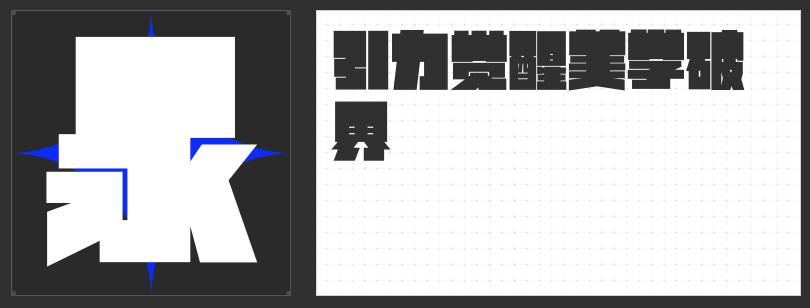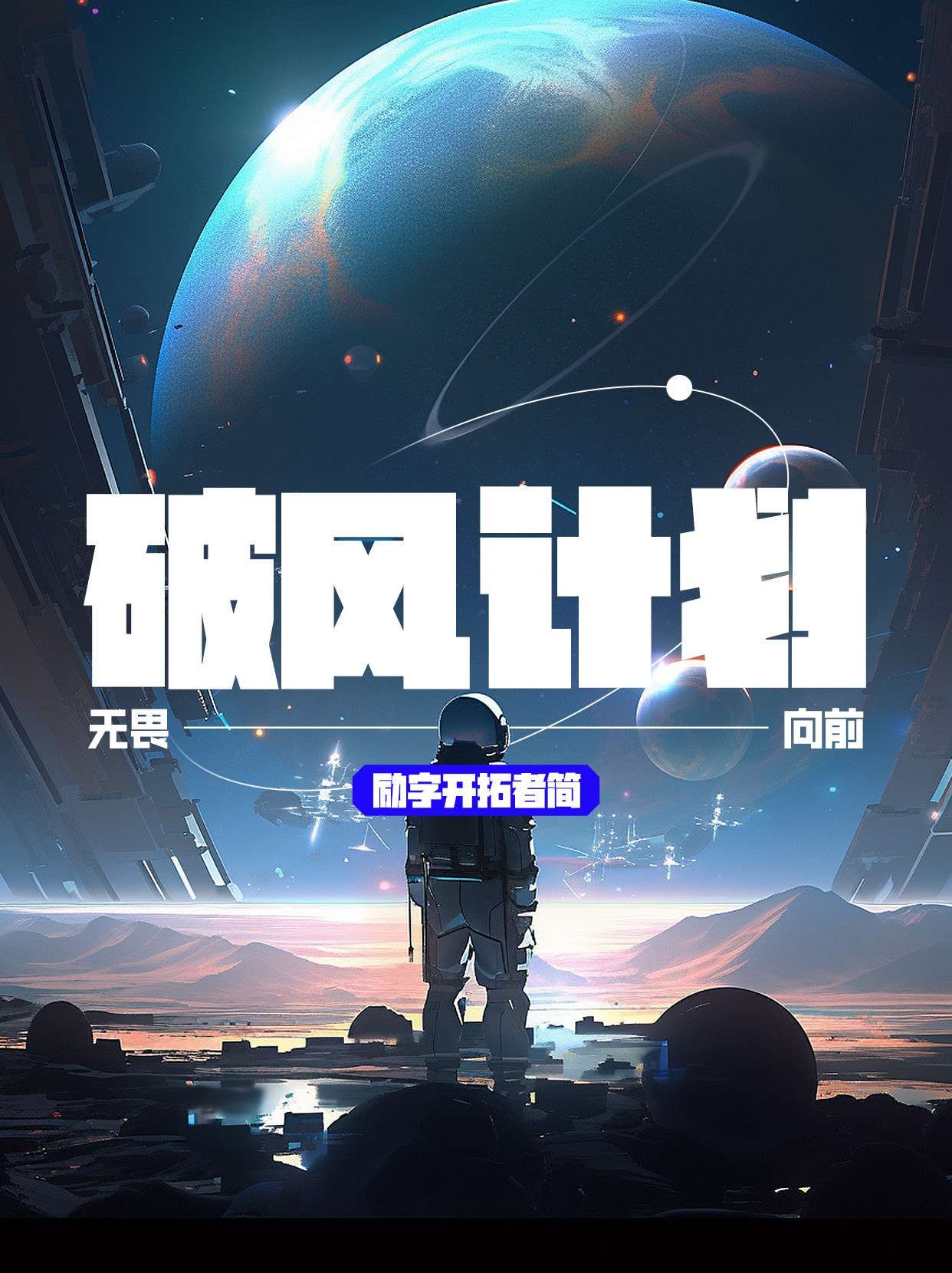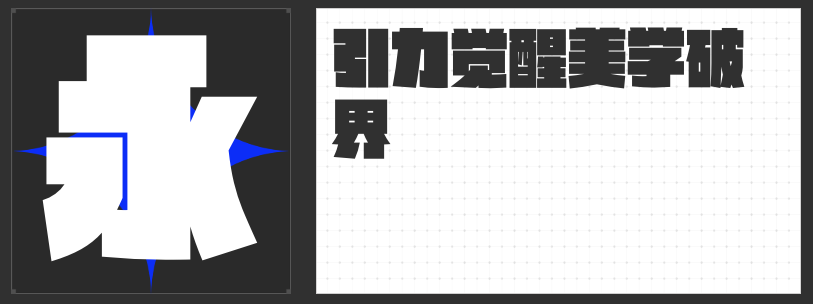
力量感爆棚!四款设计必备强势字体推荐
在设计中,字体不仅仅是文字的载体,更是传递情感与氛围的关键元素。今天,为大家推荐四款充满力量感的字体,它们不仅具备强烈的视觉冲击力,还能在设计中增添一份独特的魅力。
这款字体以其方正的字型和较大的中宫设计,展现出一种稳重的力量感。笔画横平竖直,棱角分明,简约而有力。特别是去钩处理后的笔画,以及竖直处理的撇、捺、点,更是带来了强烈的镜像视觉效果,让文字仿佛拥有了生命。此外,它还包含了众多网红流行用字,如“又、双、叒、叕”等,让你的设计更加紧跟潮流。
这款字体以其独特的反差设计,打破了传统字体的束缚。顶部加粗、底部减细的设计,使得字体在视觉上更具张力,仿佛每一笔都蕴含着无穷的力量。笔画夸张而棱角分明,重心平稳,让人一眼难忘。
这款创意黑体字,以其粗壮的笔画和宽大的字面,犹如铁拳出击,横扫千军。饱满的块面感和折角圆设计,更是让字体在视觉上更具冲击力。无论是用于标题还是正文,都能迅速抓住观众的眼球。
这款字体字型饱满,字面率高达90%左右,中宫宽大,布白均匀。在保留文字识别性的基础上,融入了流畅的曲线笔画,使得整体更加硬朗而有力。钩笔画和弯钩笔画的微向上抬设计,以及斜切处理的收笔,更是为字体增添了一份灵动与活力。
这四款字体各具特色,无论是哪一款,都能为你的设计增添一份独特的力量感。不妨在下次设计中尝试一下,相信它们一定会给你带来意想不到的惊喜!